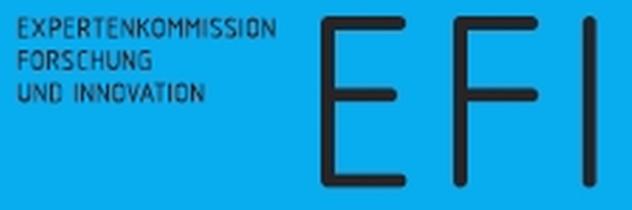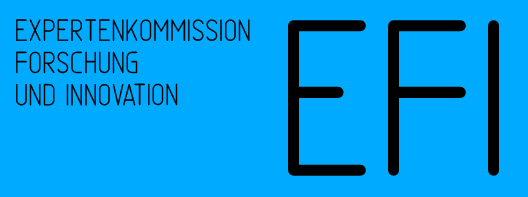
Welche Schrift ist das? (EFI)
weiß jemand was das für eine Schrift ist?
Die hatte ich zu Beginn auch auf dem Schirm. Aber die Gravur passt nicht. Vergleiche u. a. mal S, C und G.
Sorry für die Überschneidung. Ich hatte es zwischenzeitlich auch bemerkt und meinen Beitrag korrigiert.
RXCBNN+Isonorm3098                   Type 1C           yes yes no      61  0
RXCBNN+Gravur-Condensed              Type 1C           yes yes yes     24  0
RXCBNN+Gravur-Condensed              Type 1C           yes yes yes     56  0
RXCBNN+Gravur-Condensed              Type 1C           yes yes yes     49  0